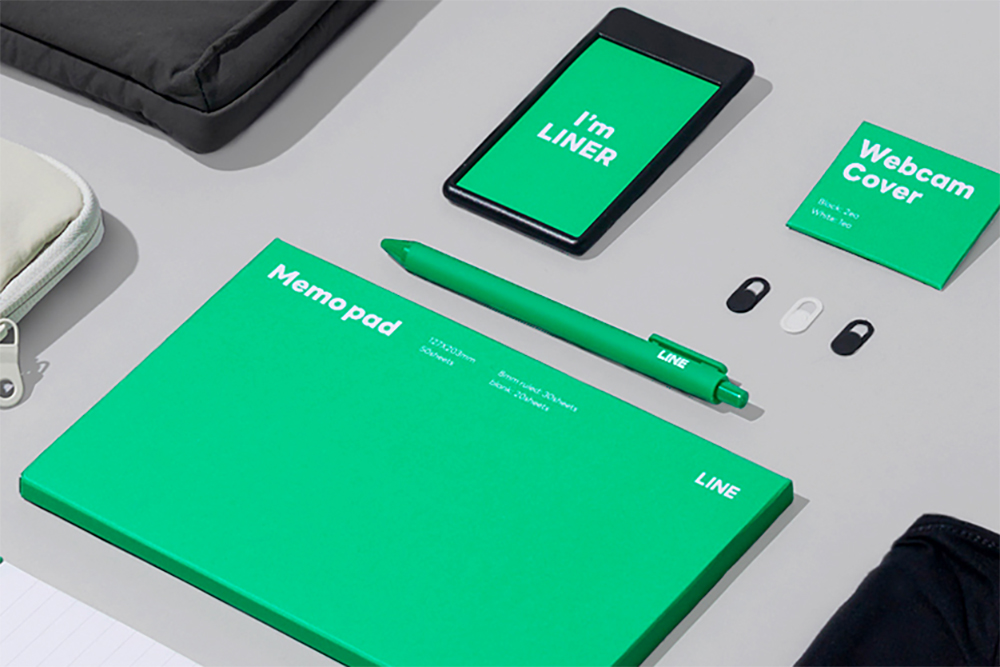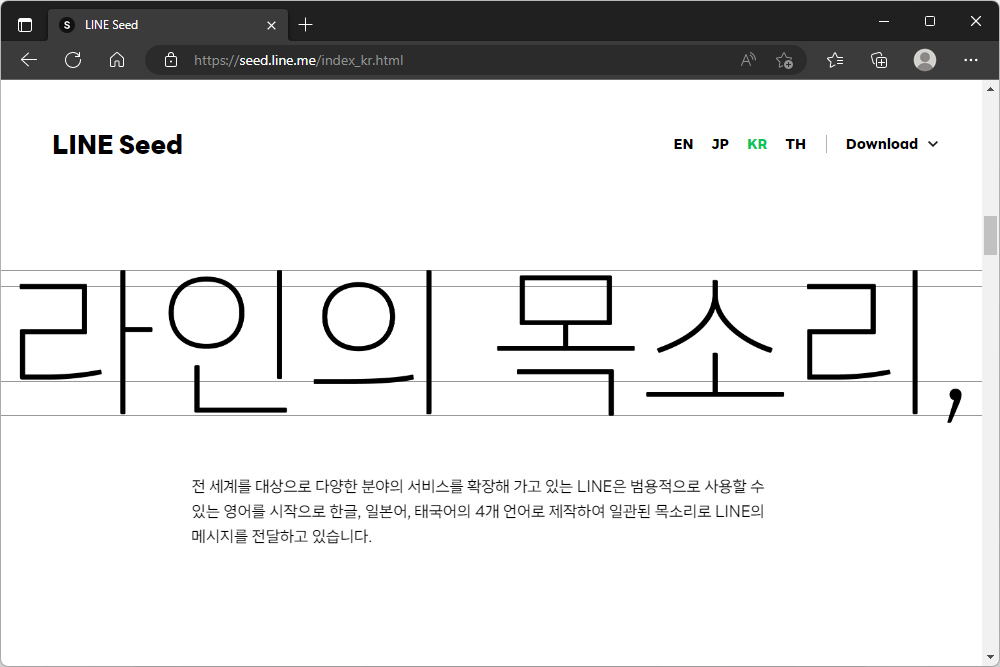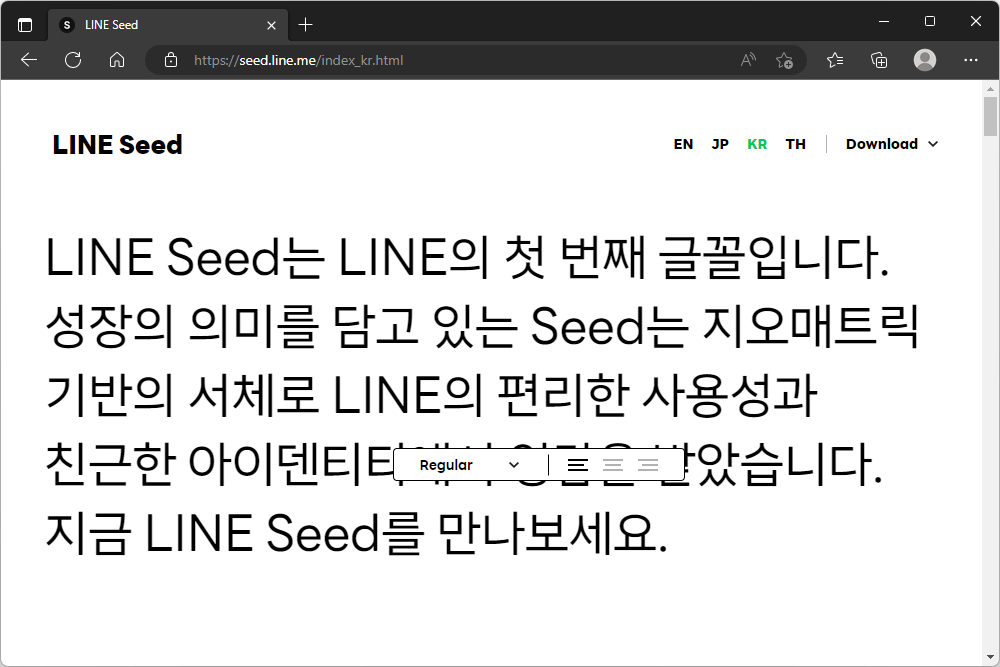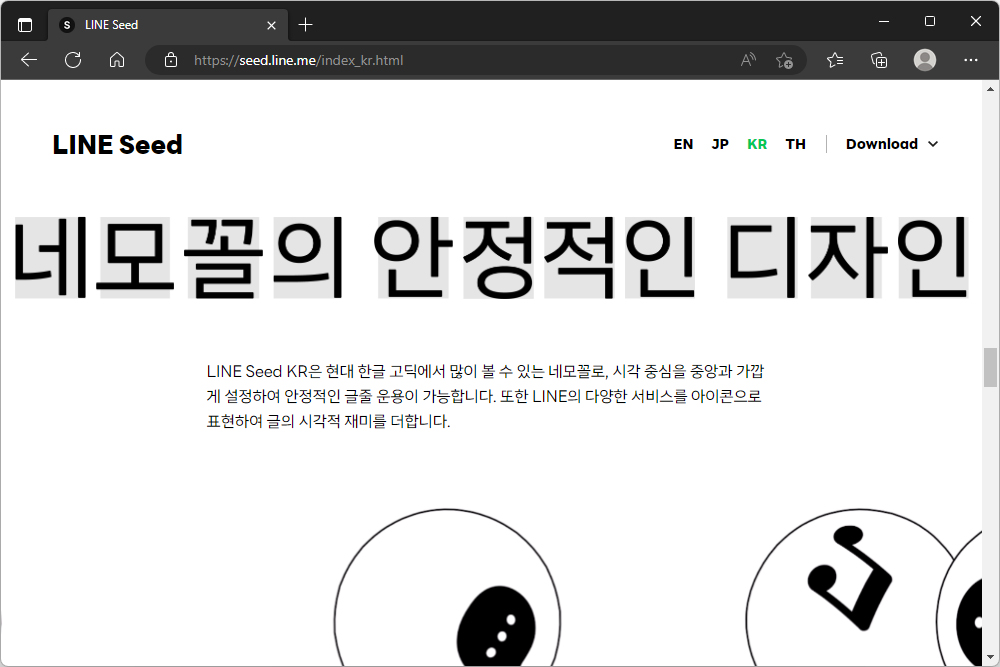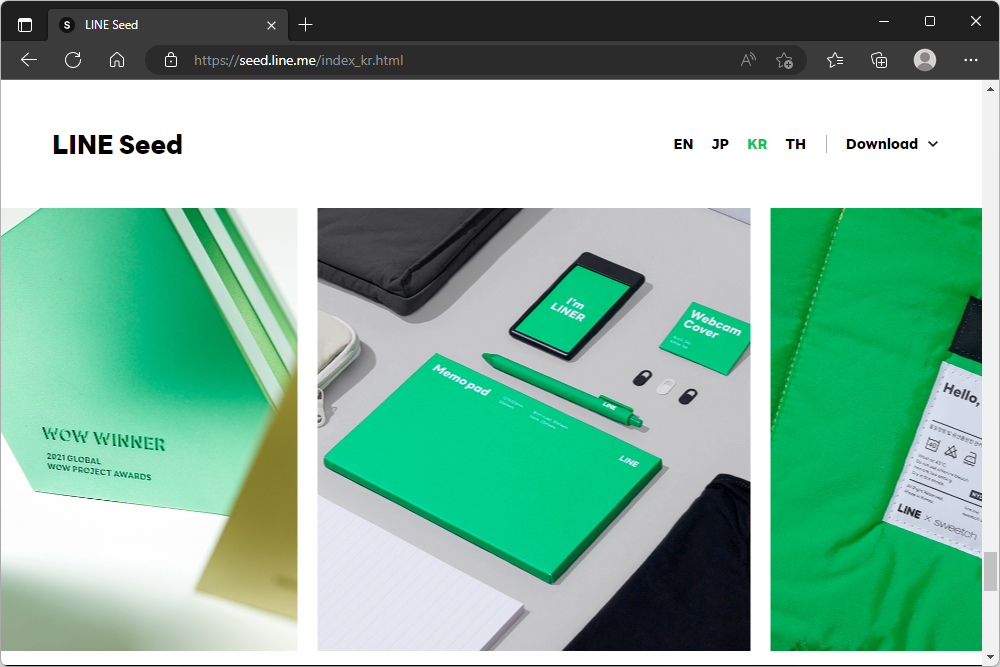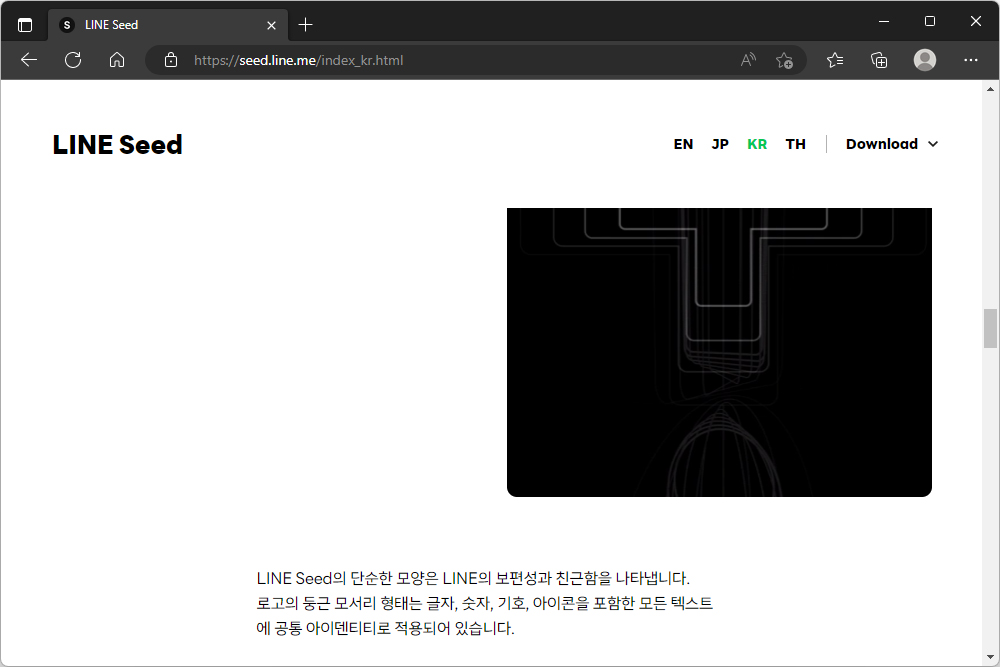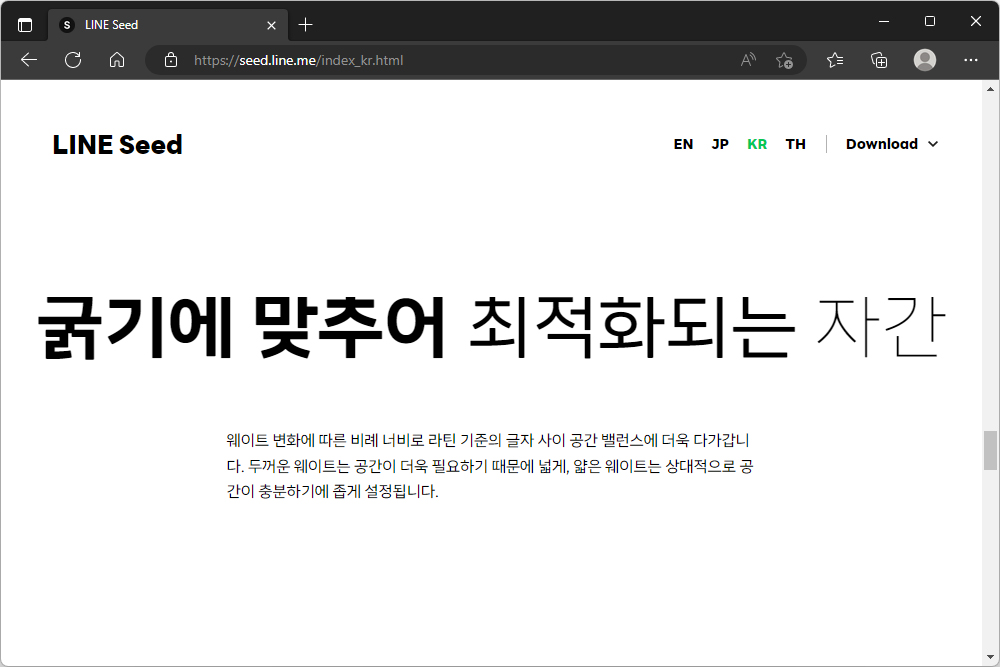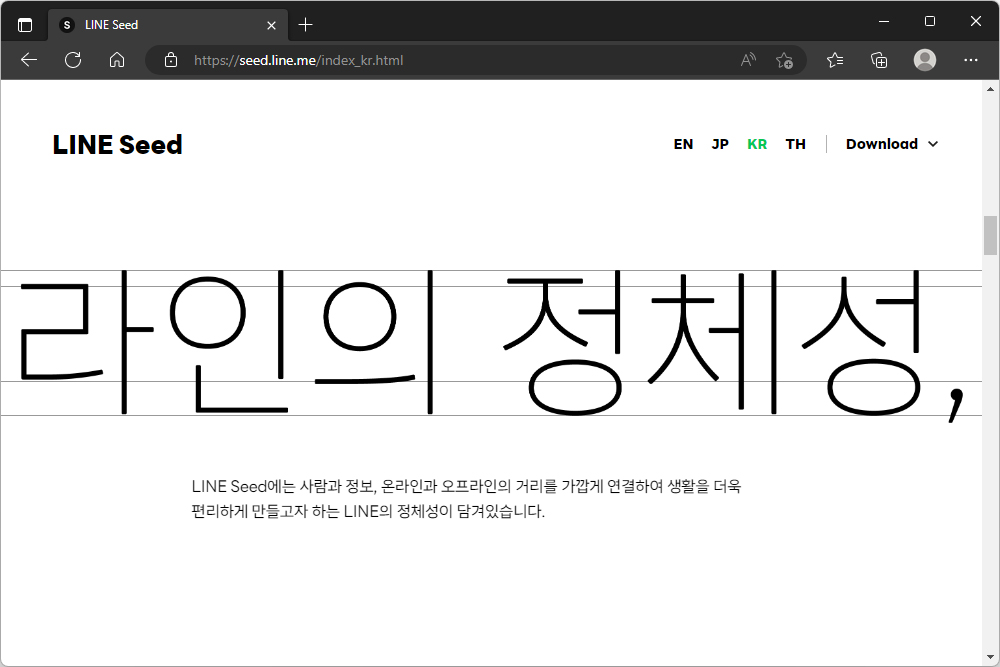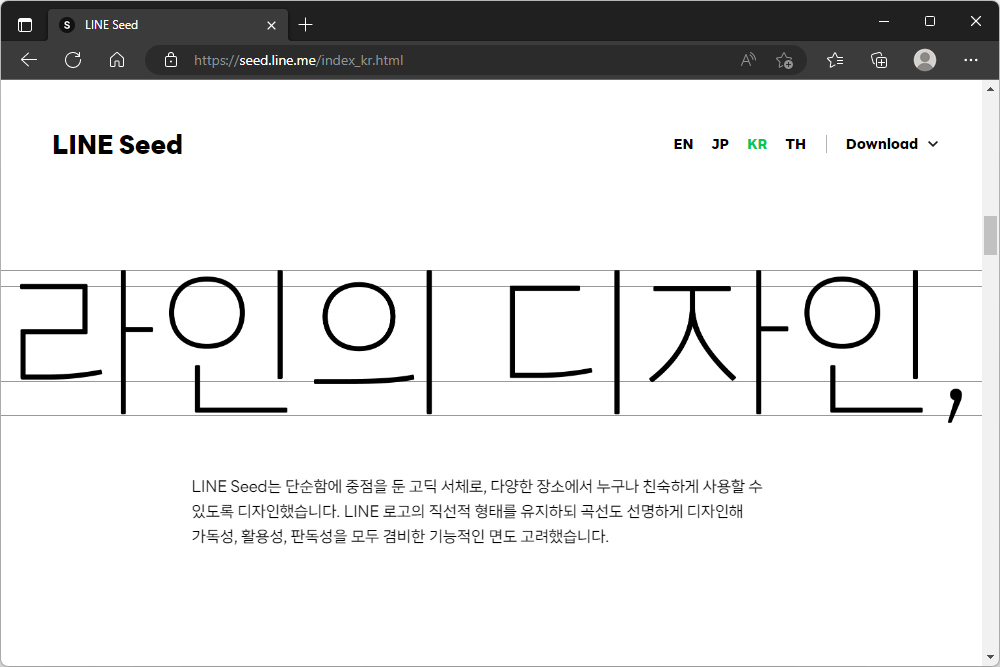
상업용 무료 폰트 라인 시드(LINE Seed) 글꼴 강력 추천!
사진이나 동영상 편집 작업을 하다 보면 가장 많이 신경이 쓰이는 부분 중의 하나는 바로 폰트의 사용입니다. 적절한 상황을 잘 표현하는 글꼴을 사용하고 싶지만, 저작권이 상당히 복잡하여서 안심하고 사용하기 어렵다는 특징이 있습니다. 그래서 상업적으로 사용할 수 있는 폰트들을 찾게 되는데요. 이번 포스팅에서는 상업적 목적으로도 사용할 수 있는 라인 시드(LINE Seed)의 특징을 자세하게 확인해 보도록 하겠습니다.
우선 아래쪽에 배치된 링크를 이용해서 라인 시드(LINE Seed) 홈페이지에 방문하면 LINE Seed 글꼴 안내 문구의 서체를 Thin, Regular, Bold 중에서 바꾸어 볼 수 있도록 구성되어 있습니다.
라인 시드(LINE Seed)의 디자인 철학을 살펴보면 우선 단순함에 중점을 둔 고딕 서체로 제작되었습니다. 전체적으로 반듯한 느낌을 주기 때문에 가독성과 활용성 그리고 판독성이 우수하다는 장점이 있습니다.
라인 시드(LINE Seed)의 또 다른 특징은 서체 안에 한글과 영어 그리고 일본어와 태국어가 포함되어 있다는 점입니다. 아무래도 라인이 전 세계에서 서비스되고 있는 메신저앱이기 때문에 관련 언어들이 탑재된 것으로 보입니다.
그리고 라인 시드(LINE Seed)는 사람과 정보 그리고 온라인과 오프라인의 거리를 가깝게 연결하여 생활을 더욱 편리하게 하지는 LINE의 정체성이 담겨있다고 합니다.
라인 시드(LINE Seed)는 둥근 모서리 형태를 가지고 있고 글자는 물론이고 숫자, 기호, 아이콘 등의 모든 텍스트에 공통적인 디자인 철학이 유지되었습니다. 상당히 신경을 많이 쓴 것으로 보입니다.
라인 시드(LINE Seed)는 한글 고딕에서 많이 보이는 네모꼴로 디자인되었습니다. 전체적으로 반듯한 느낌을 주기 때문에 제목은 물론이고 본문 등에 사용해도 위화감이 적은 편입니다.
그리고 라인 시드(LINE Seed)는 굵기에 따라서 자간이 최적화되는 형태로 제작되었습니다. 그래서 정밀하게 편집할 필요가 적은 편입니다. 운근히 편리한 부분이라고 할 수 있습니다.
라인 시드(LINE Seed)는 단순히 온라인에서는 물론이고 오프라인에서 각종 굿즈를 만들 때 활용해도 좋을 정도라고 생각되었습니다. 그런데 이 부분의 라이센스는 한 번 확인해 보는 것이 좋을 것 같습니다.
라인 시드(LINE Seed)는 반듯한 고딕 스타일로 제작되어서 제목이나 본문 등 다양한 용도로 활용할 수 있다는 장점이 있습니다. 그래서 각종 편집물이나 각종 물건을 제조할 때 필요한 폰트가 필요한 분들은 라인 시드(LINE Seed)를 활용해 보시길 바랍니다.